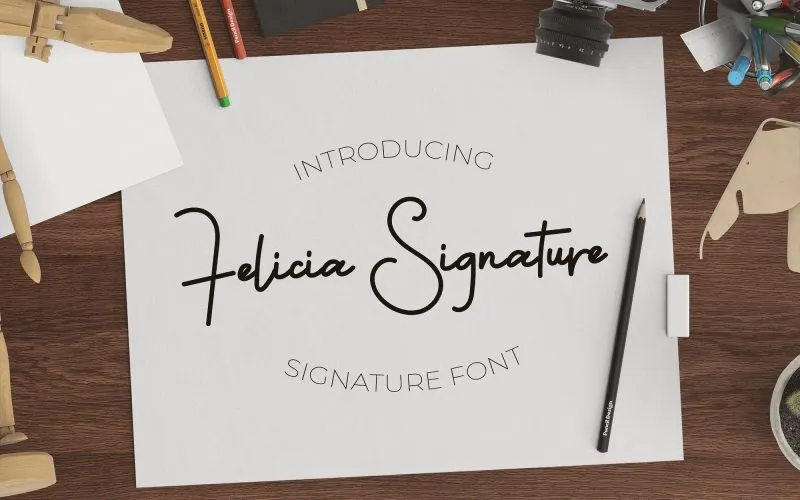
Felicia Signature Font – Download Grátis
Aqui está uma versão em português do Brasil de 2 parágrafos curtos para a descrição da fonte ‘Felicia Signature Font’, respeitando as instruções fornecidas: Vamos explorar um novo recurso que poderá revolucionar seu trabalho de design: a ‘Felicia Signature Font’. Introduzida pelo designer Vasgaz Creative, esta fonte está pensada especificamente para aqueles que buscam uma escrita moderna e única. Ideal tanto para assinaturas pessoais quanto para títulos em livros ou revistas, este é um recurso indispensável para qualquer profissional de design que valoriza a personalização ao máximo. Com seu feitio aparentemente realista, esta fonte permite aos artistas digitais criar uma escrita autêntica e impressionante. Além disso, possui alternativas de swash (esforços extras na letra) e ligação de caracteres (ligações automáticas entre letras adjacentes). Estas opções adicionam um toque único que certamente tornará seus trabalhos ainda mais distintos. A ‘Felicia Signature Font’ é perfeitamente adaptada para qualquer aplicação que valorize a autenticidade da escrita manuscrita. Seja em uma capa de livro, uma encomenda ou até mesmo na impressão de um cartão de aniversário – esta fonte irá garantir que o seu trabalho seja inovador e memorável.